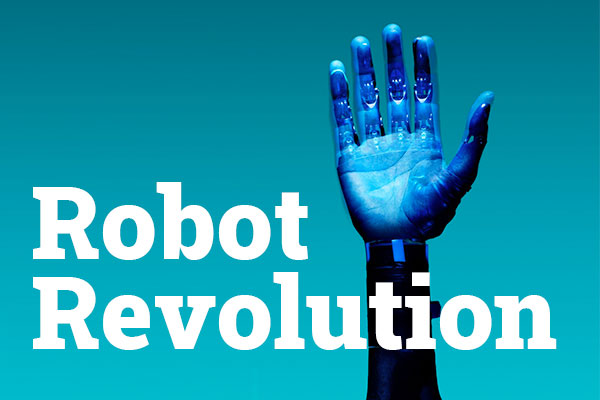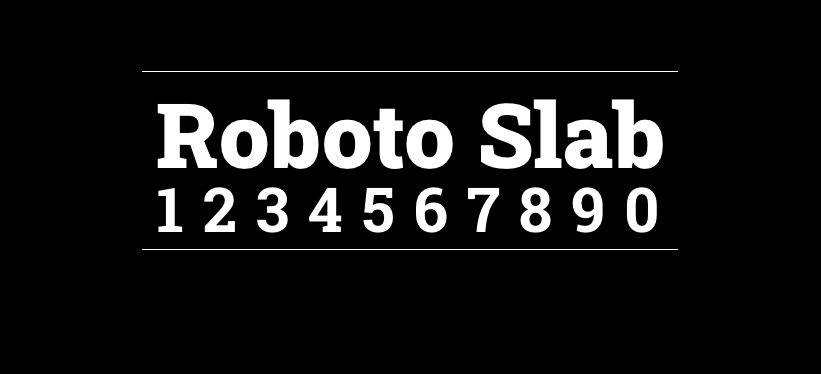
Roboto Slab
Roboto Slab是Christian Robertson设计的一款英文衬线字体,该字体隶书Roboto字体家族,该字体具有友好且开放的曲线。虽然有些怪诞的字母扭曲了他们的字母形状以迫使其具有僵化的节奏,但是Roboto并没有妥协,允许字母以其自然宽度来固定。这使得更自然的阅读节奏在人文主义和衬线字体类型中更为常见。